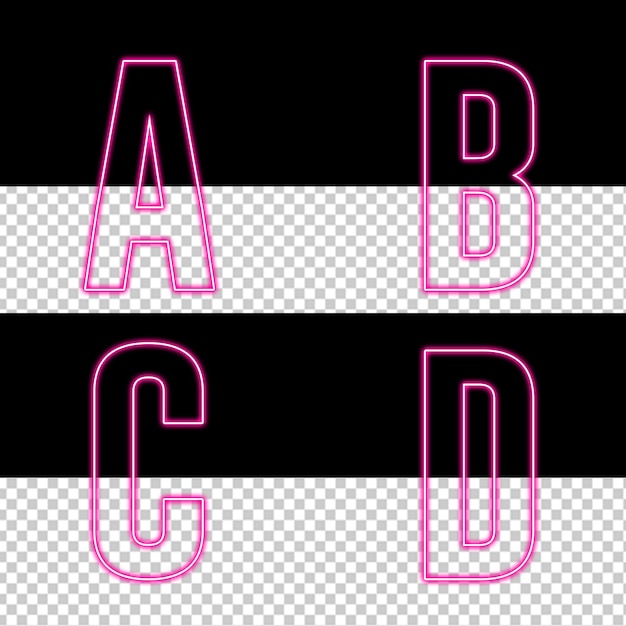
alfabet ABC неоновый текст накладка неоновое освещение Литерный корпус Шрифт неоновый световой эффект слово английский effe
Alfabet ABC неоновый текст накладка неоновое освещение Литерный корпус Шрифт неоновый световой эффект слово английский effe